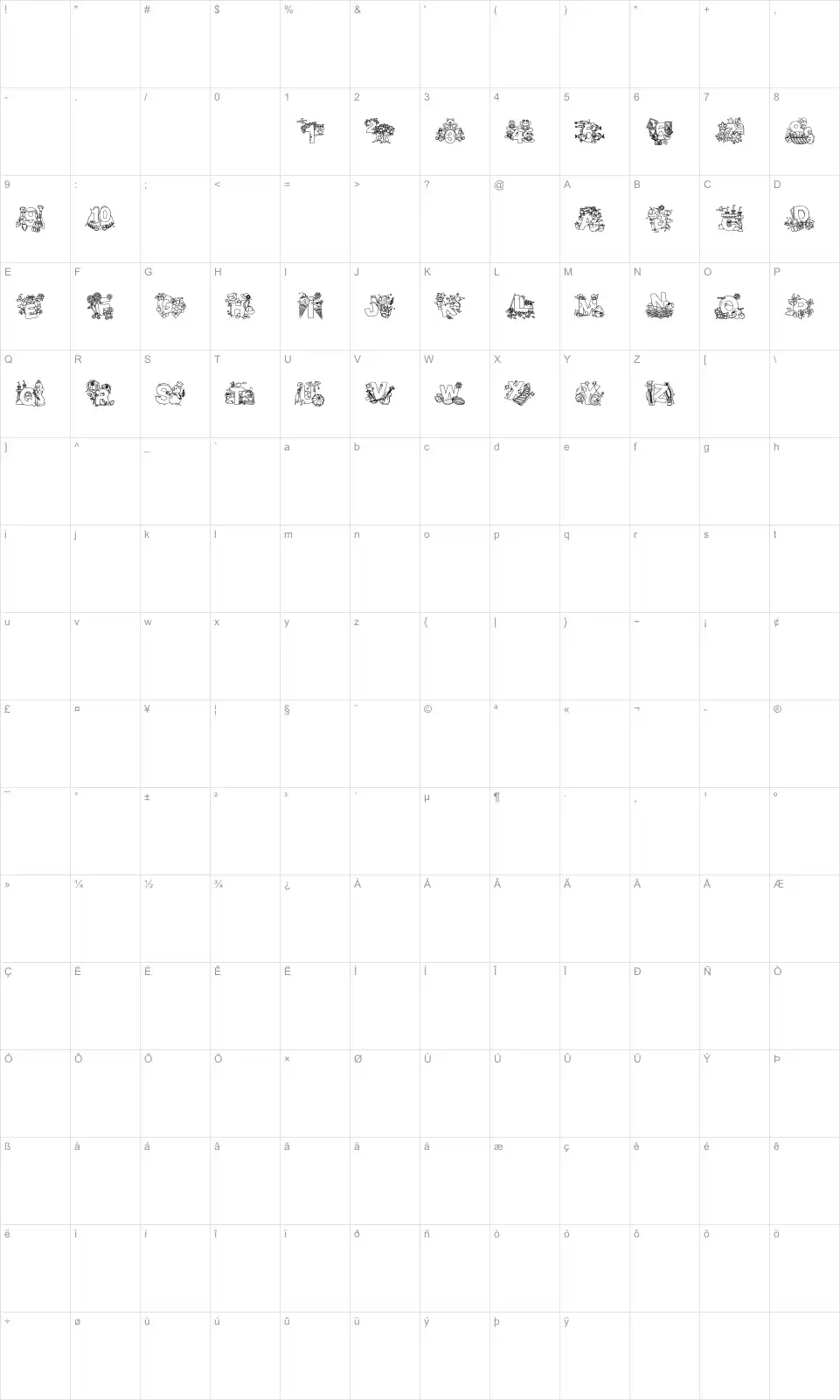
Crayola Kiddy Font – Download Grátis
A fonte Crayola Kiddy Font, criada pela House of Lime, é ideal para quem procura uma fonte divertida e adequada para crianças. Esta fonte Dingbat está disponível para download gratuitamente para uso pessoal e pode ser usada para criar um preview de texto personalizado online antes de ser utilizada. Sua categoria Kids lhe dá uma ideia de como ela se destina a ser usada em projetos para crianças. Adicionada em 12 de julho de 2022, esta fonte já foi baixada por 2813 pessoas, indicando a sua popularidade. Com um tamanho de 138 KB, ela é uma opção compacta e fácil de usar. Para mais informações ou para acessar a fonte diretamente, você pode visitar o site oficial da House of Lime, http://www.houseoflime.com.